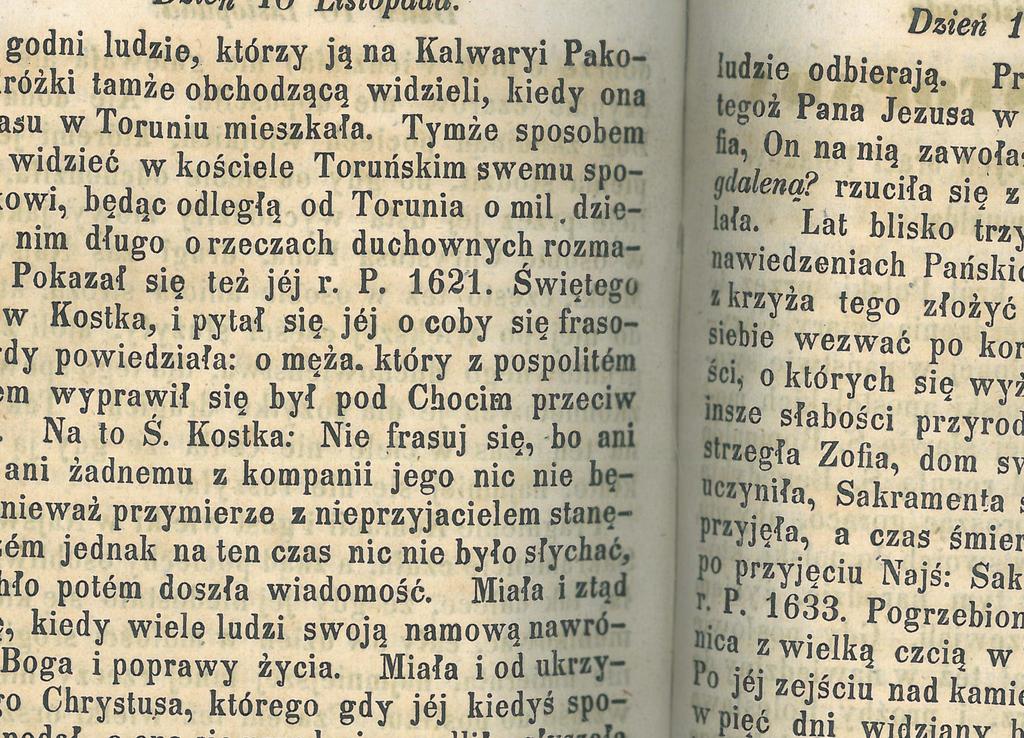
Heneczek jest fontem wykonanym w ramach programu Patriotyzm jutra dla Miejskiej Biblioteki Publicznej w Piekarach Śląskich. Font zrodził się w
1 Heneczek
2 Heneczek jest fontem wykonanym w ramach programu Patriotyzm jutra dla Miejskiej Biblioteki Publicznej w Piekarach Śląskich. Font zrodził się w związku z 200. rocznicą urodzin drukarza Teodora Heneczka ( ) Font powstał na podstawie czcionki używanej w drukach wykonanych przez Teodora Heneczka. Czcionka posiadała wiele sprzecznych elementów jak np. wąską minuskułe i szerszą majuskułe i wersaliki. Część cech czcionki została odrobinę złagodzona aby poprawić jej czytelność, orginalne diakrytyki zostały jednak pozostawione z możliwością wyboru współczesnych diakrytyków w zestawie stylistycznym. Ponieważ wykonane miały być tylko znaki ograniczonego do języka polskiego i ew. niemieckiegofont dopiero będzię uzupełniony o roserzony zestaw znaków po publikacji Heneczka Pro publikowanego w Threedotstype.